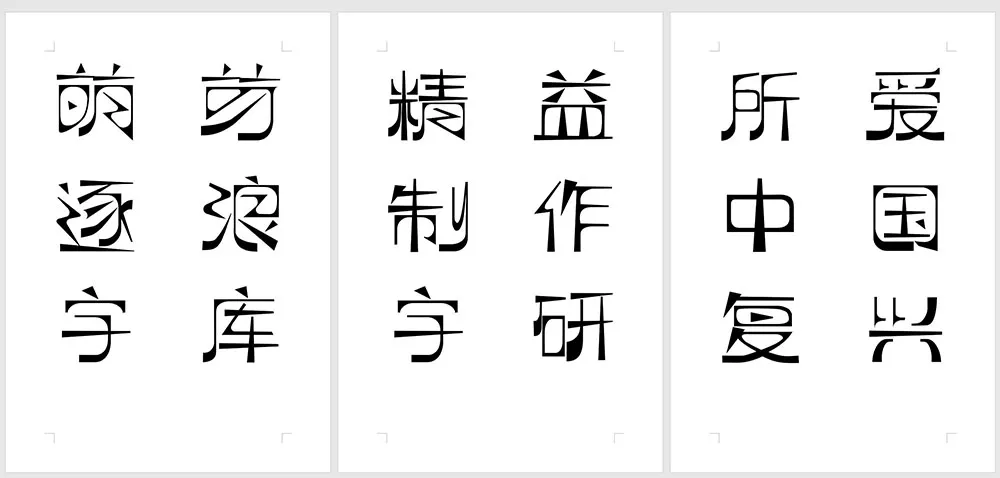
一款參照借鑑近代中國共產黨《萌芽》月刊的藝術字體,一套優秀的中文字庫,逐浪字庫團隊出品,中文字形部份符合中華人民共和國GB2312規範,英文與拉丁字形符合GoogleFonts開源規範。
源自五四運動文化,力求體現近代文藝風。字體線條呈現外方內圓格局,有尖銳的外角、三角部件,而內部空間則呈現圓形切割效果。這體現了五四、清末民初,在工業革命思維衝擊下,一代文化人對於中國漢字的探索。又似布爾什維克人的工人、工業文化在漢字下的體現。尖銳、銳角三角形的部件,從中體現了上進、革命、進擊。結字扁形,即左右寬度大於上下高度。
1.外角採用尖角,內角採用弧角
2.是一個抽象的孤形字。
3.試圖創造上個世紀30年代“左聯”的手寫字體風格,該風格是用於出版物出版,簡樸又不失藝術性。
4.多弧形、多三角形。
5.整體偏矮寬方正型,非常規字體,異型字居多
6.筆畫粗細對比明顯,角的筆畫相對橫豎線要粗
7.豎線筆畫下端粗上端細,橫線筆畫左邊粗右邊細
8.外角整體偏方形,內角整體偏圓形的創意字體
9.整體風格硬朗纖細
創作筆記:一款字體,從前期創意,到基本造型,再到合成編程,再到優化出版。最少需要3-5個月。同時發佈後還要針對各個場景進行修正優化,這是一個漫長的過程。所以中國古代有“倉頡造字,鬼神哭”的說法。